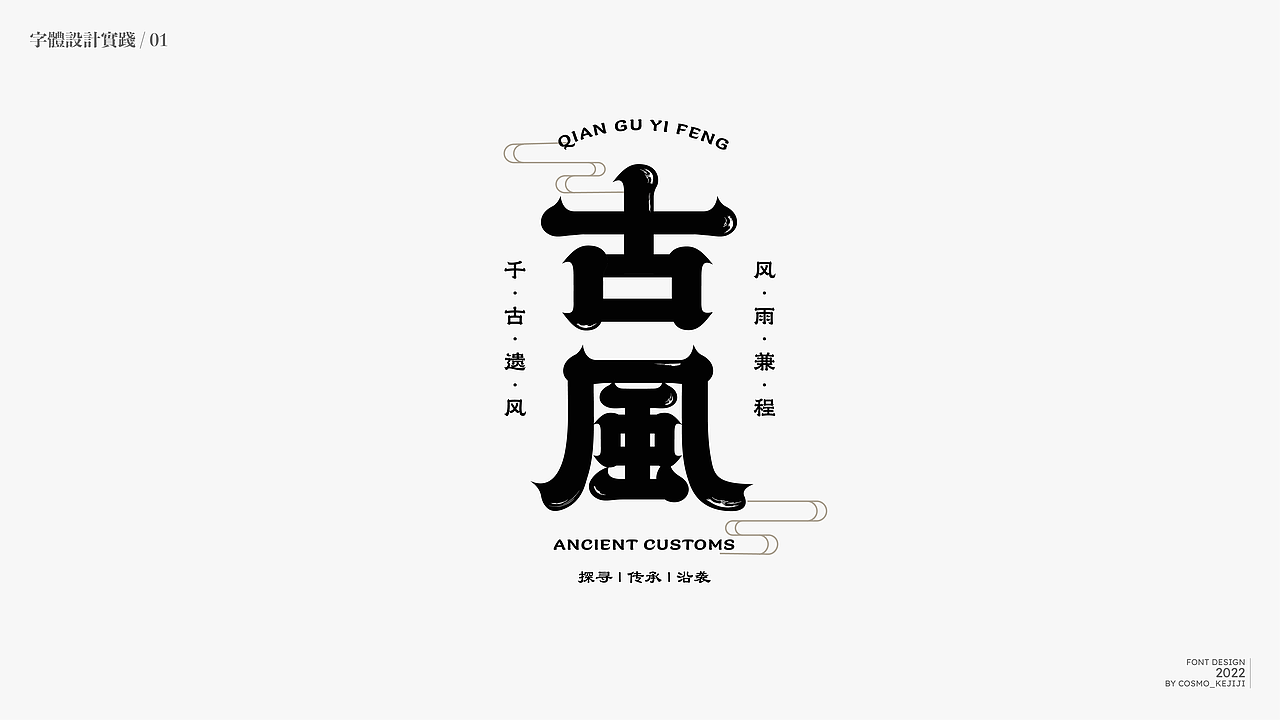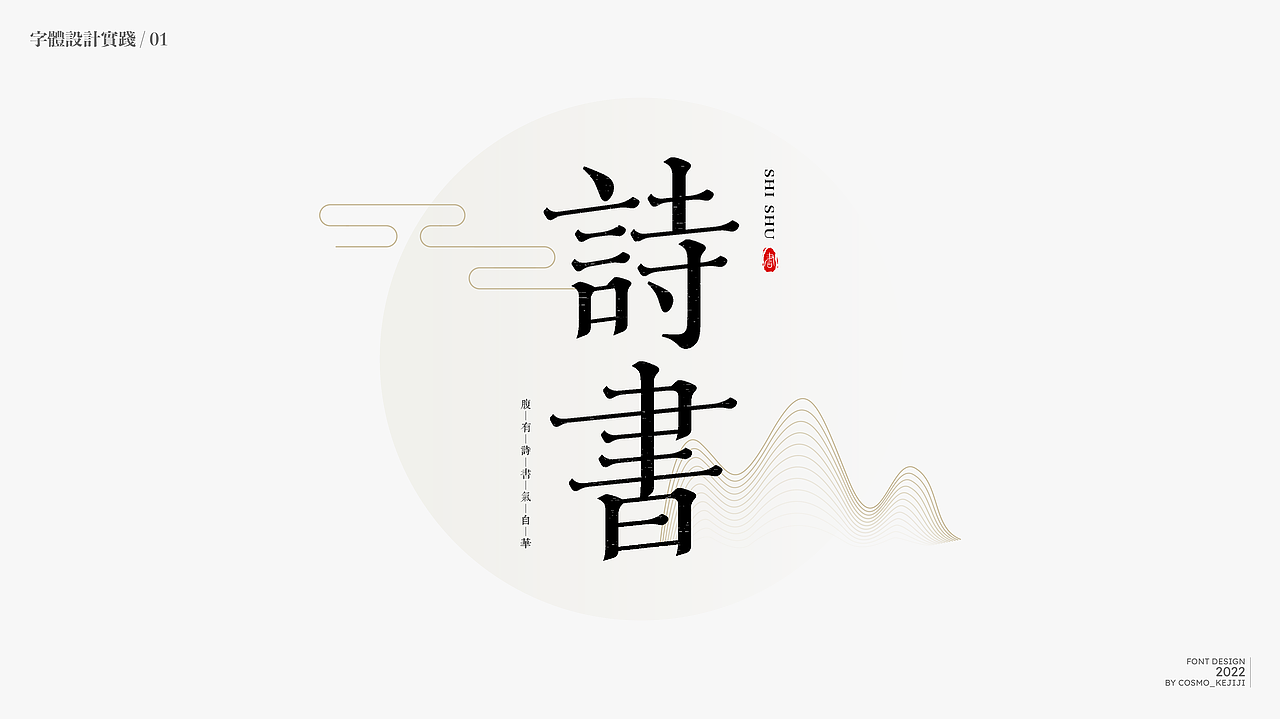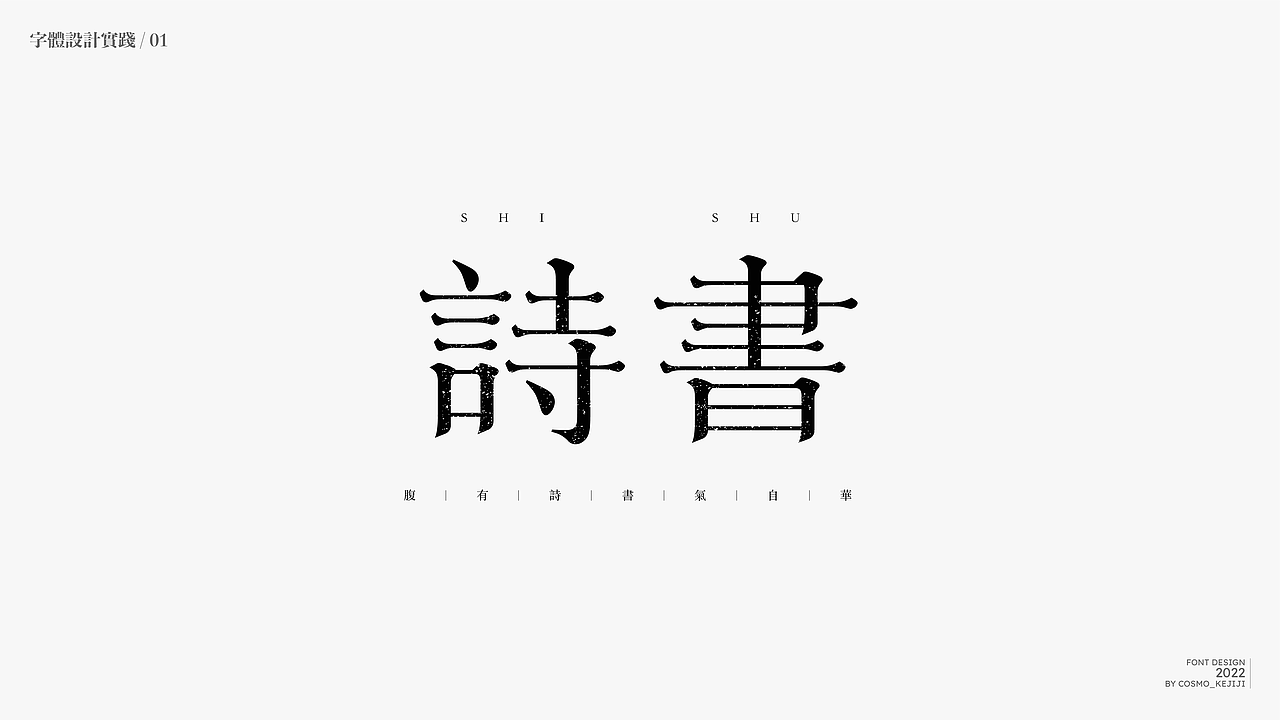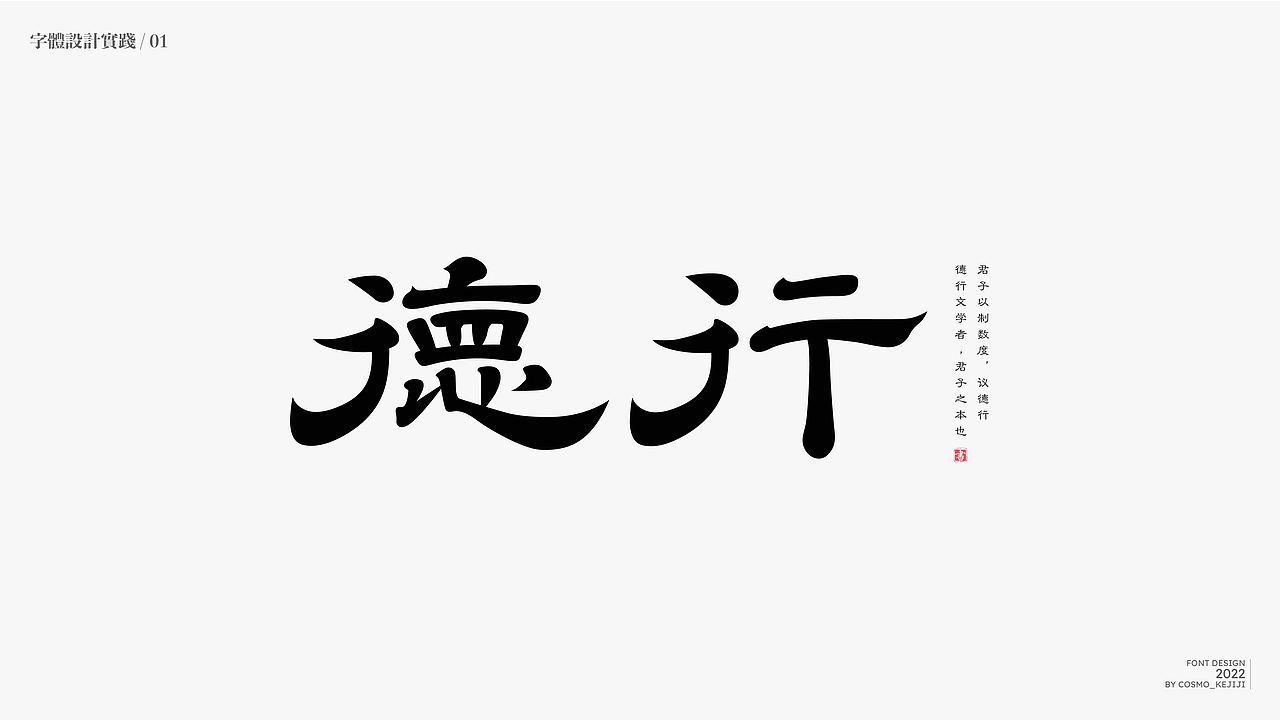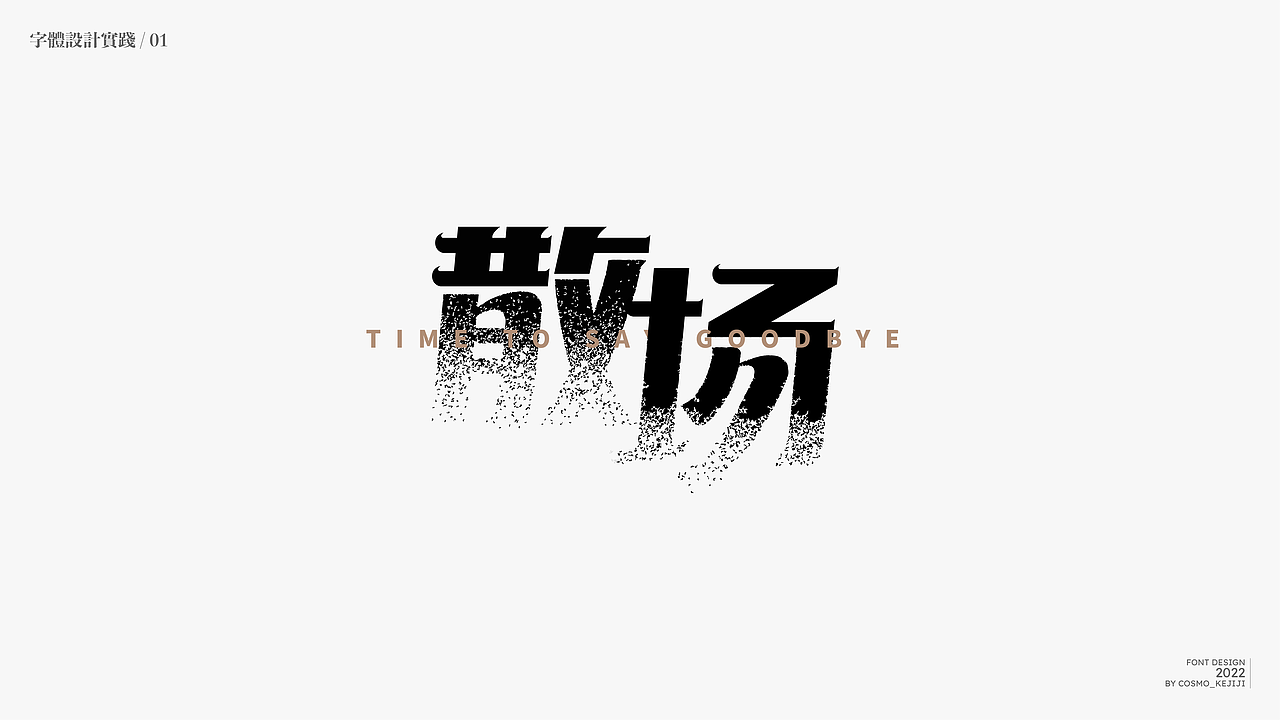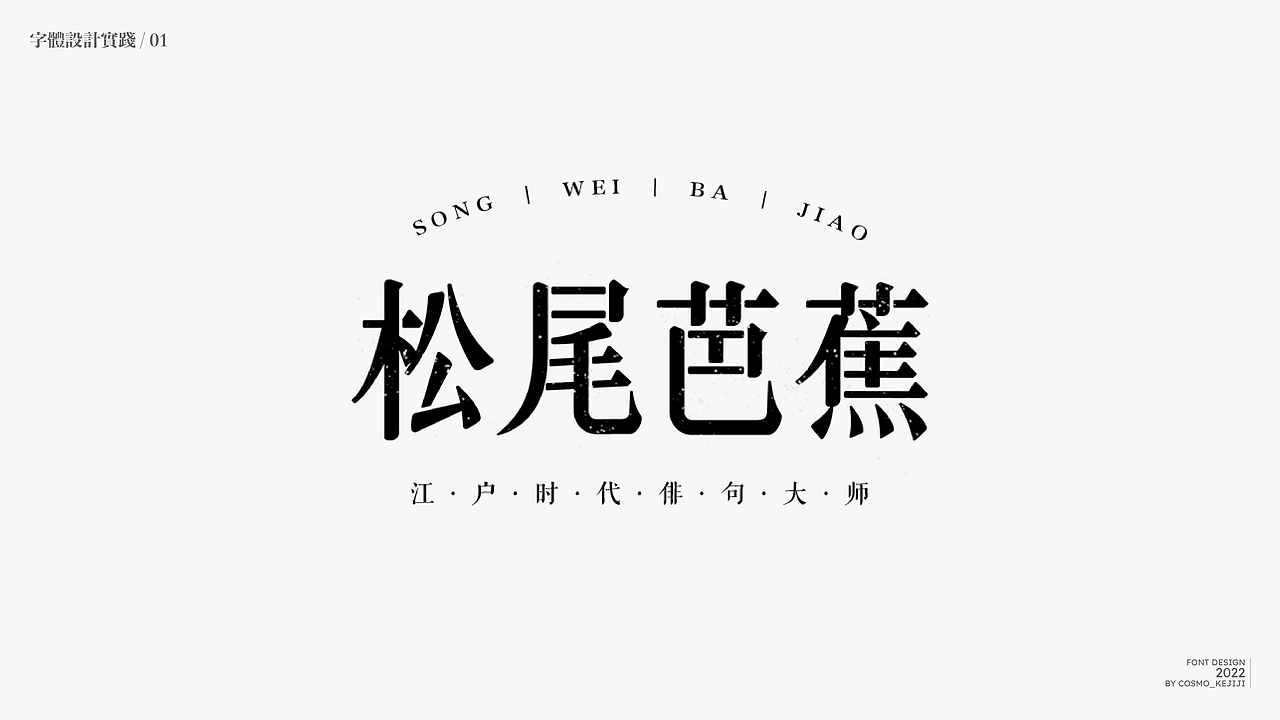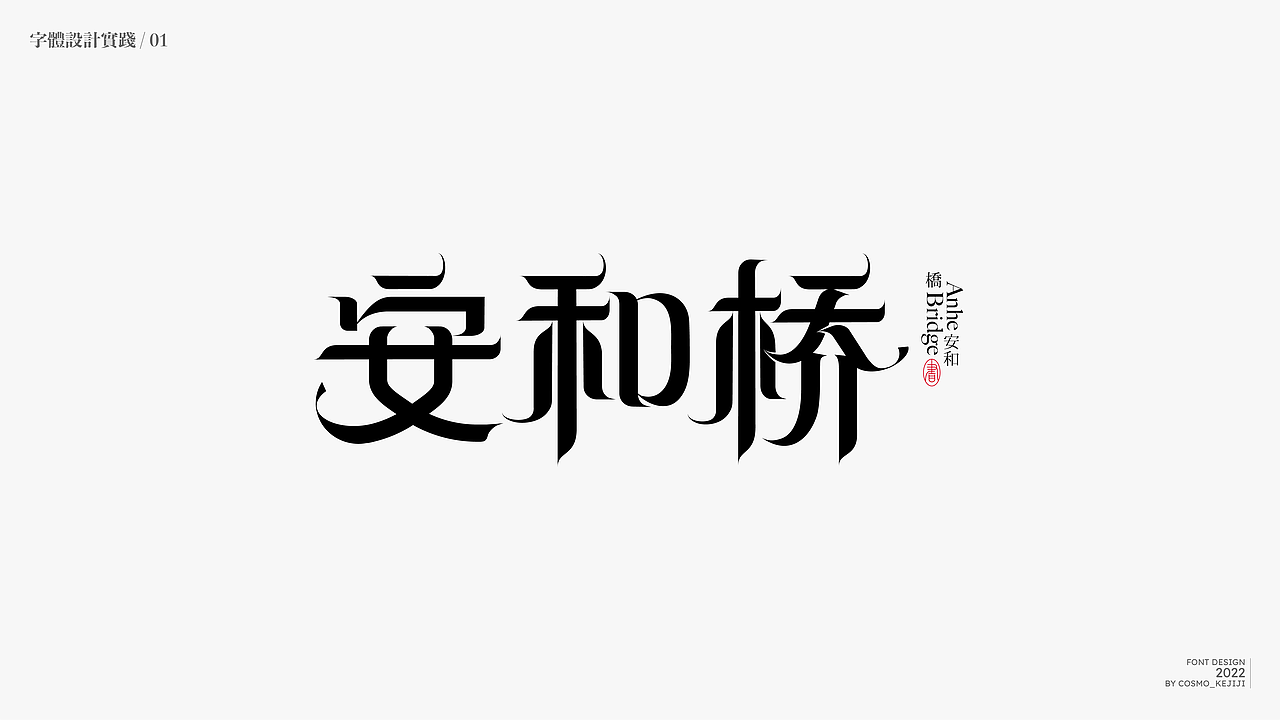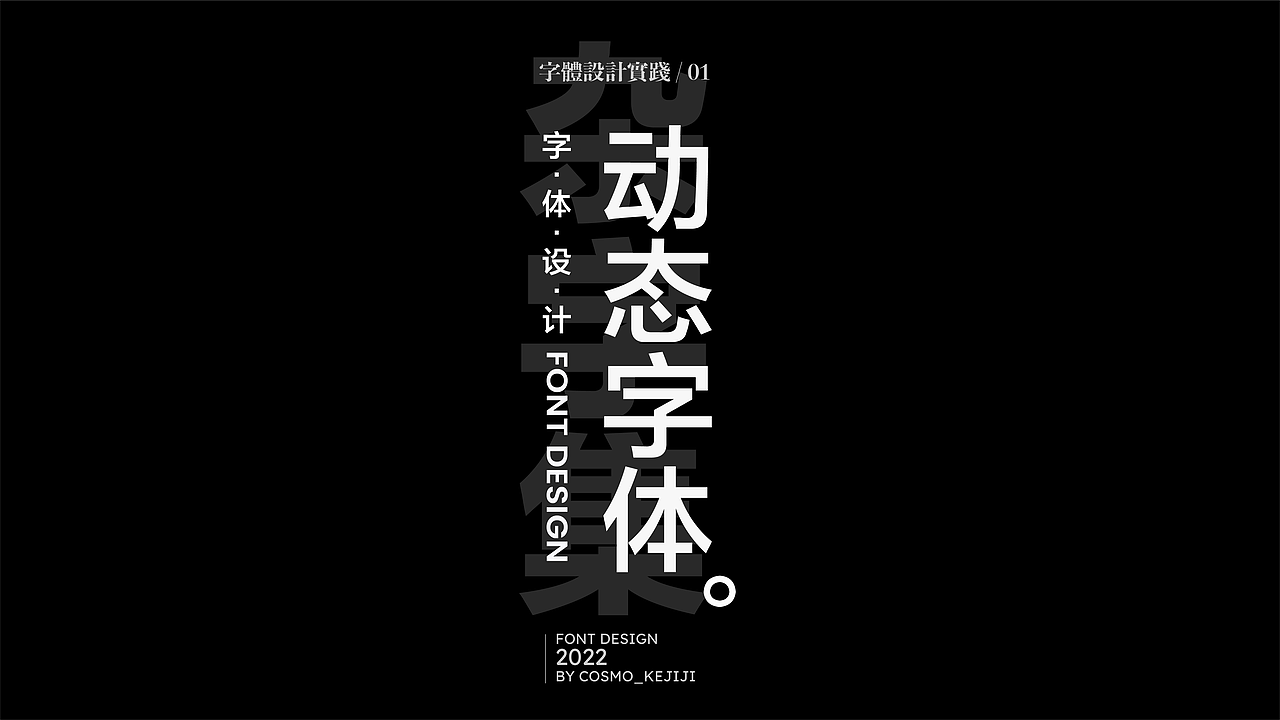
杂字集 | 字体设计实践练习
-用这个作品来作为字体设计和平面设计的入门吧,今年最大的收获应该就是解锁了设计的新方向,传统的古代字形真的太博大精深。
-跟着课程学下来尝试了不同类型的字体,就算是总结一下吧,猴子老师说的对,“字体设计入门简单,做好了难。” 其实每一种设计都一样,有很多不足,希望可以坚持下去,一直进步。